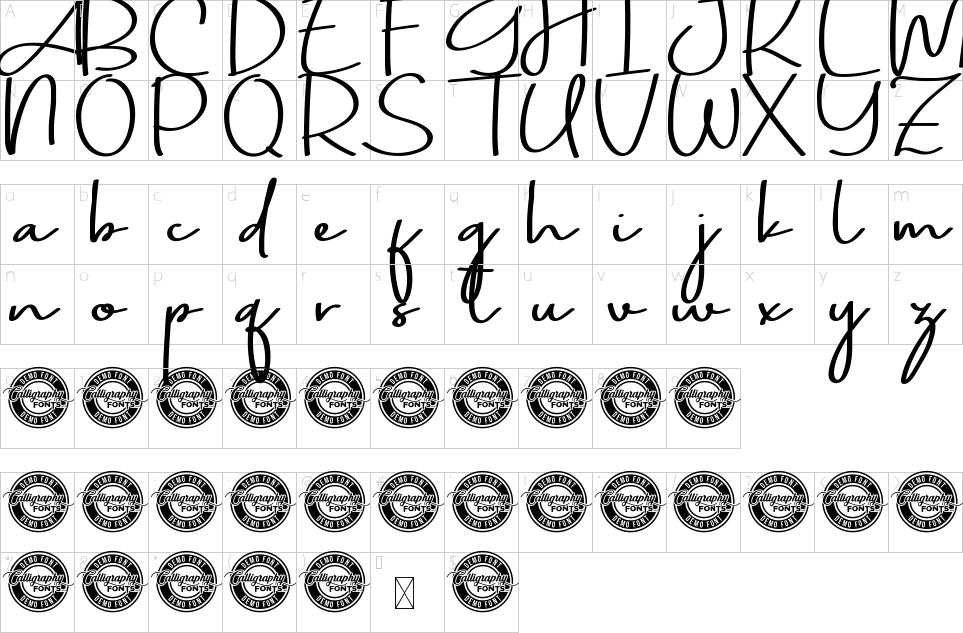
Aqui está uma versão curta e envolvente para a descrição de uma página de download da fonte ‘Grinadine Madalie Font – 1001 Free Fonts’: Descubra um novo estilo para seus projetos com Grinadine Madalie. Essa elegante font foi criada pela equipe da CalligraphyFonts e já tem mais de quinhentas pessoas baixando-a. Com sua graça sofisticada, esta é uma ótima escolha para personalizar seu design ou até mesmo criar um logotipo atraente. Com o seu download gratuito da Grinadine Madalie Font, você pode trazer uma atmosfera única e sofisticada aos seus projetos. Seja em seu site, aplicativo móvel ou documentos de trabalho, essa font leva seu design para o próximo nível. Não deixe de experimentar a diferença que esse belo recurso gráfico pode fazer!